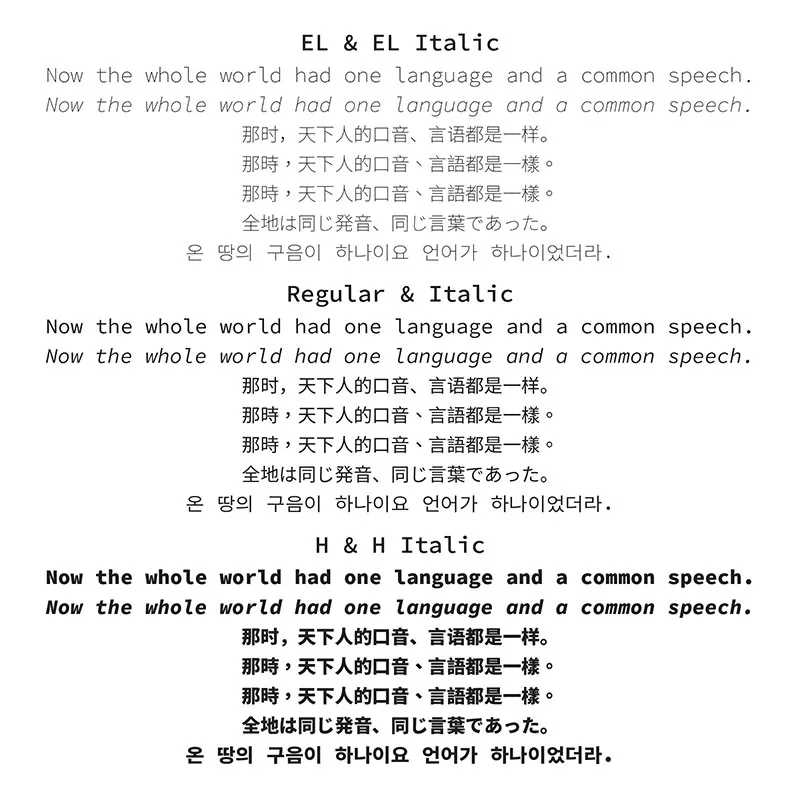
思源等寬(Source Han Mono,源ノ等幅)源於思源黑體(Source Han Sans)和Source Code Pro,是一個OpenType/CFF集合(OTC),包括70個字體實例,由七個權重、五種語言和兩種樣式組成,是Source Han Code JP的泛CJK版本。與思源黑體、思源宋體一樣,通過 SIL OFL 授權協議發佈。
思源等寬是從 Source Han Code JP(源ノ角ゴシック Code)發展而來的,西文部分從 Source Code Pro 修改而來,漢字、假名部分則直接從思源黑體拿過來(半角假名、諺文需要適當修改)。思源等寬 1.000 與思源黑體 2.001 在字重、支持語言方面一致,但出於「編程字體」的考慮,思源黑體中一些用不到編程裡的字形就沒有收錄,這為西文斜體騰出了空間。
字形設計方面,有七個字重(EL、L、N、R、M、B、H),有五種語言(日、韓、簡中、繁中臺灣、繁中香港),西文部分有正體與斜體。